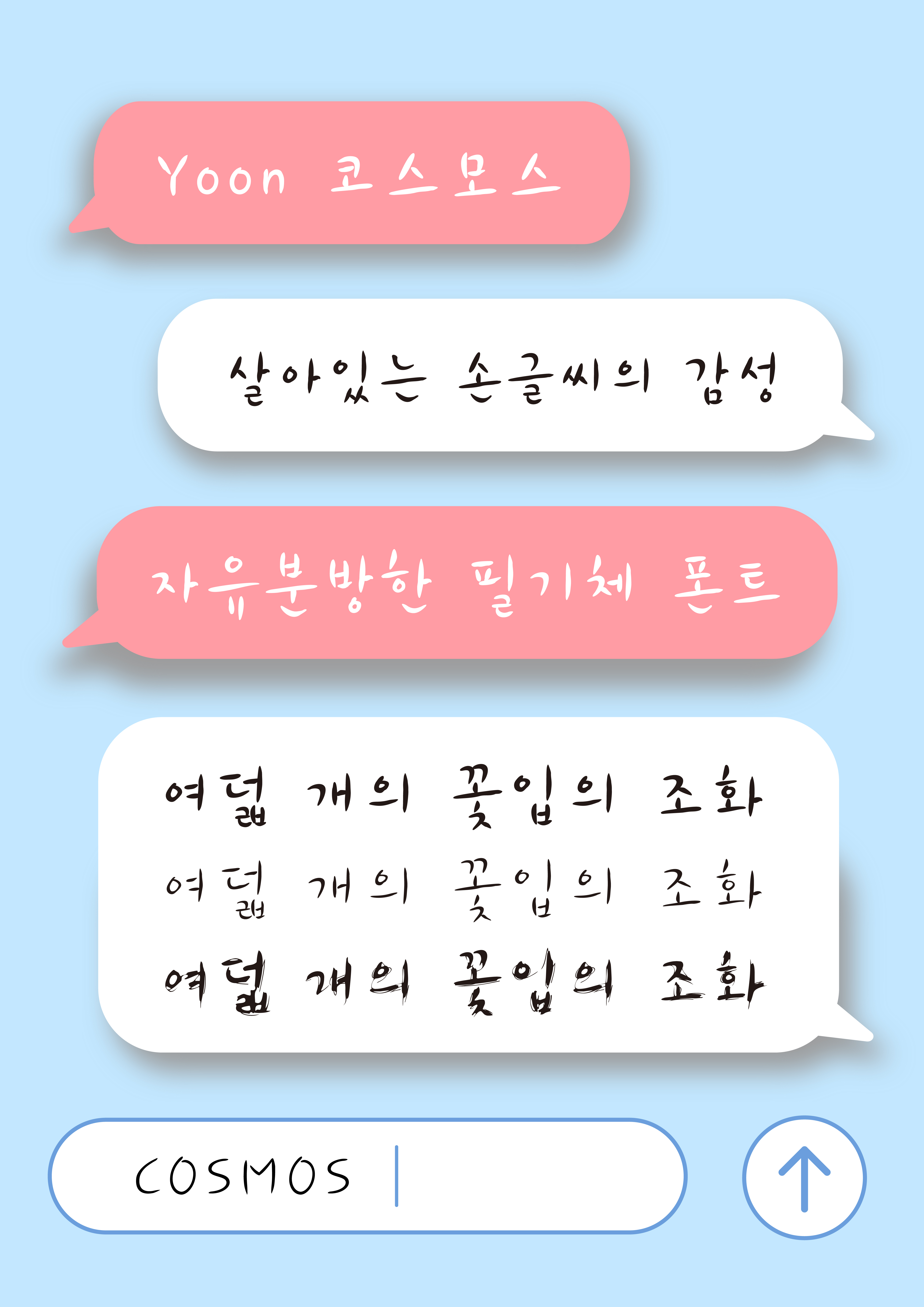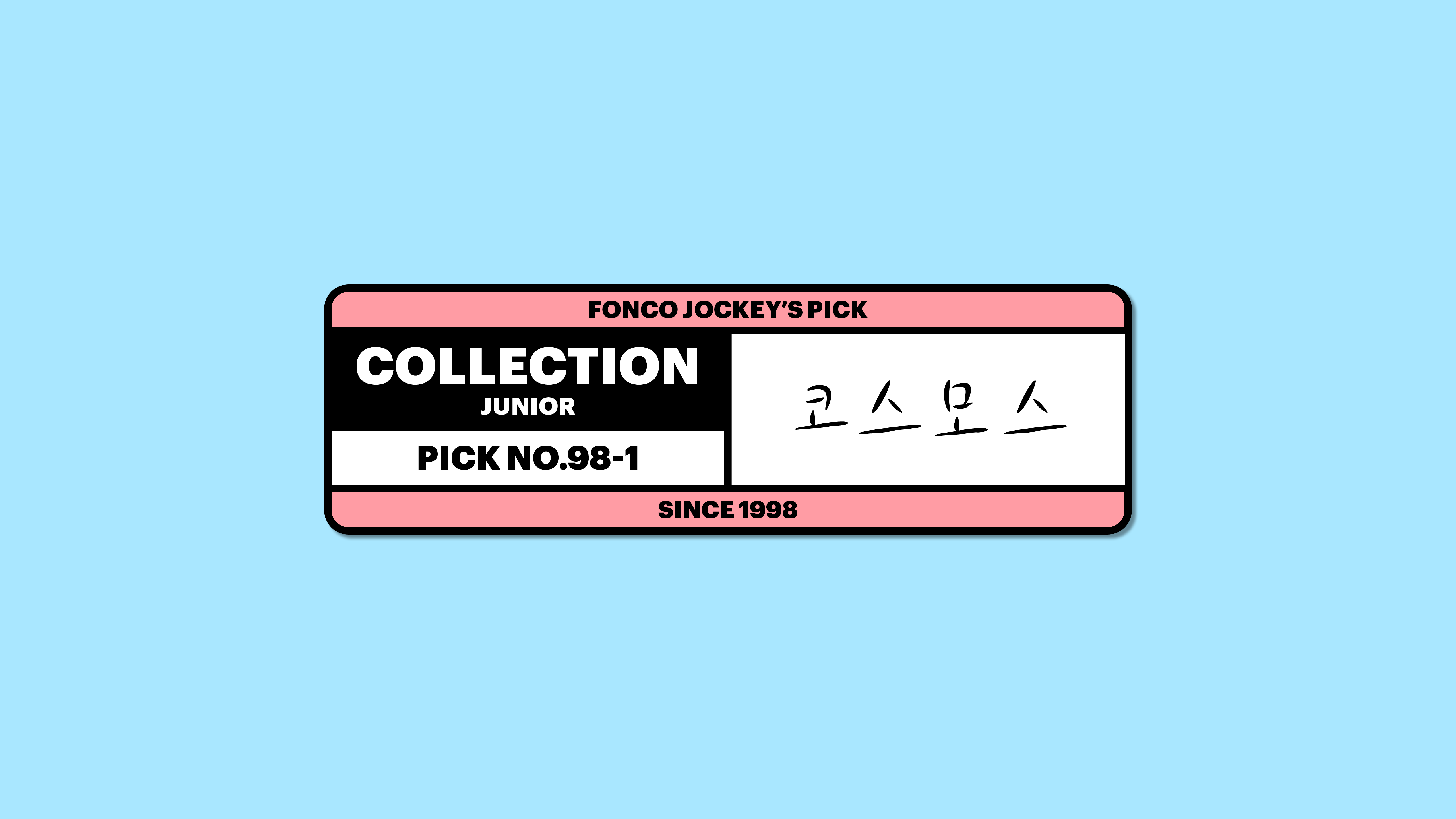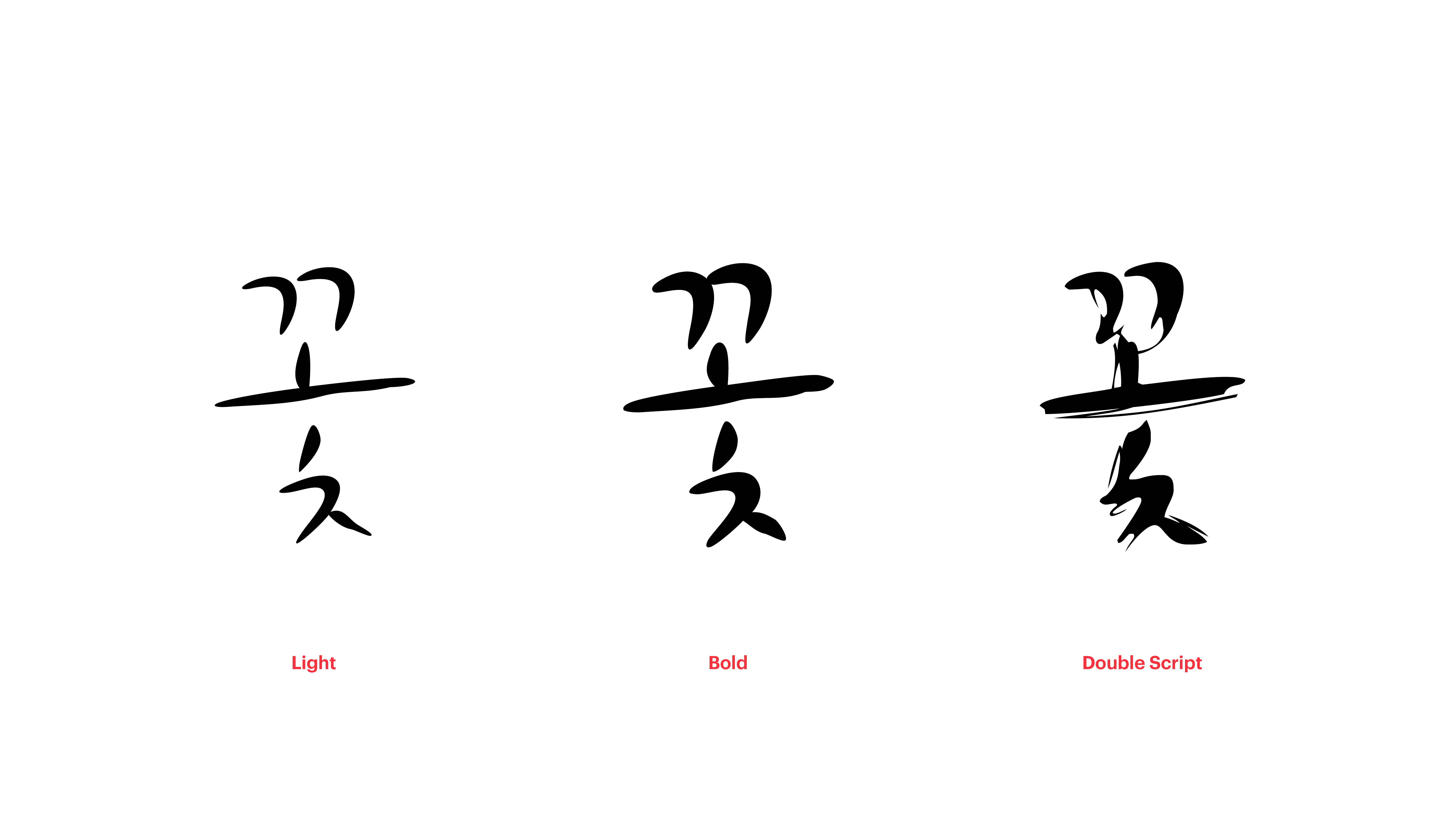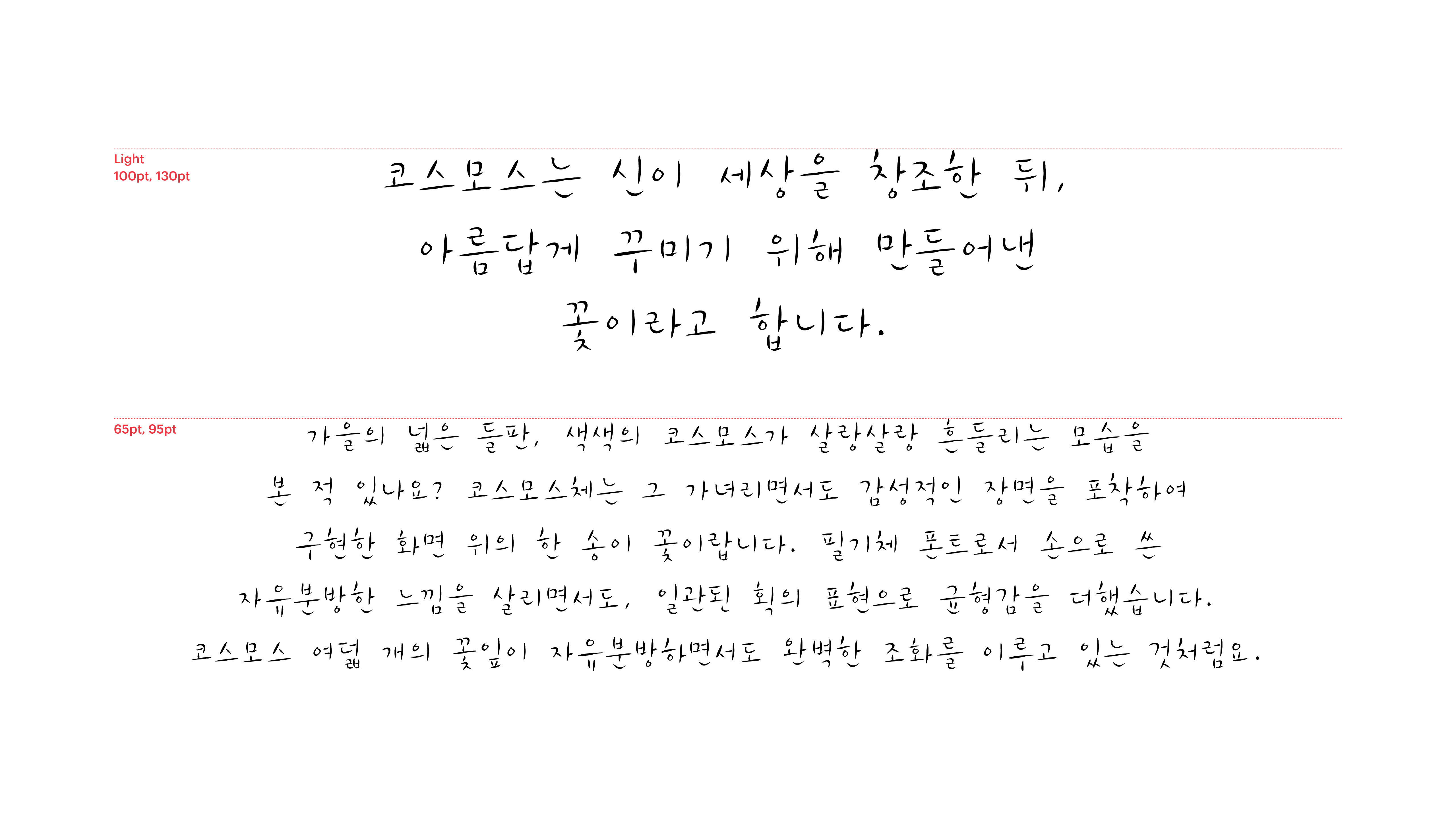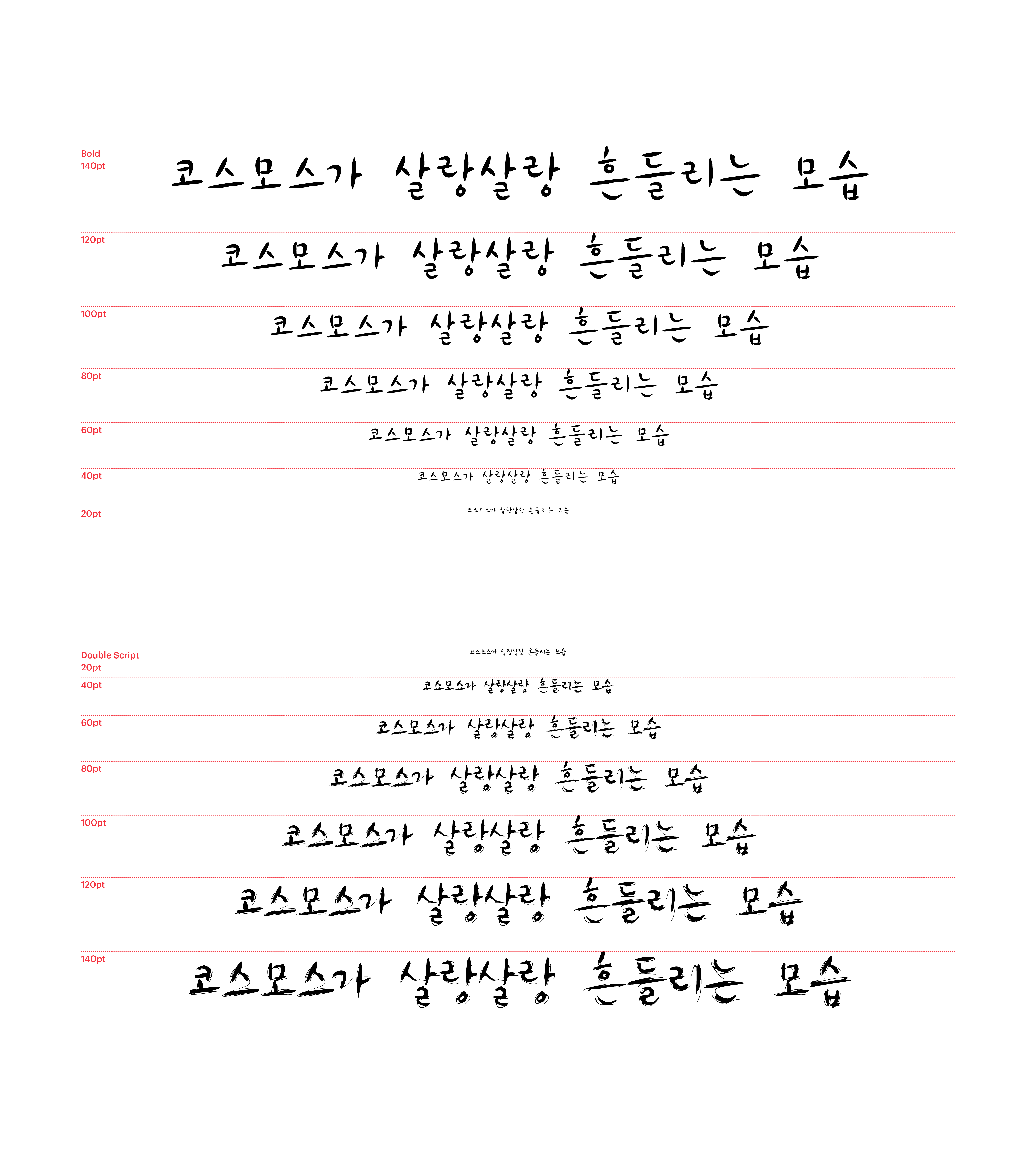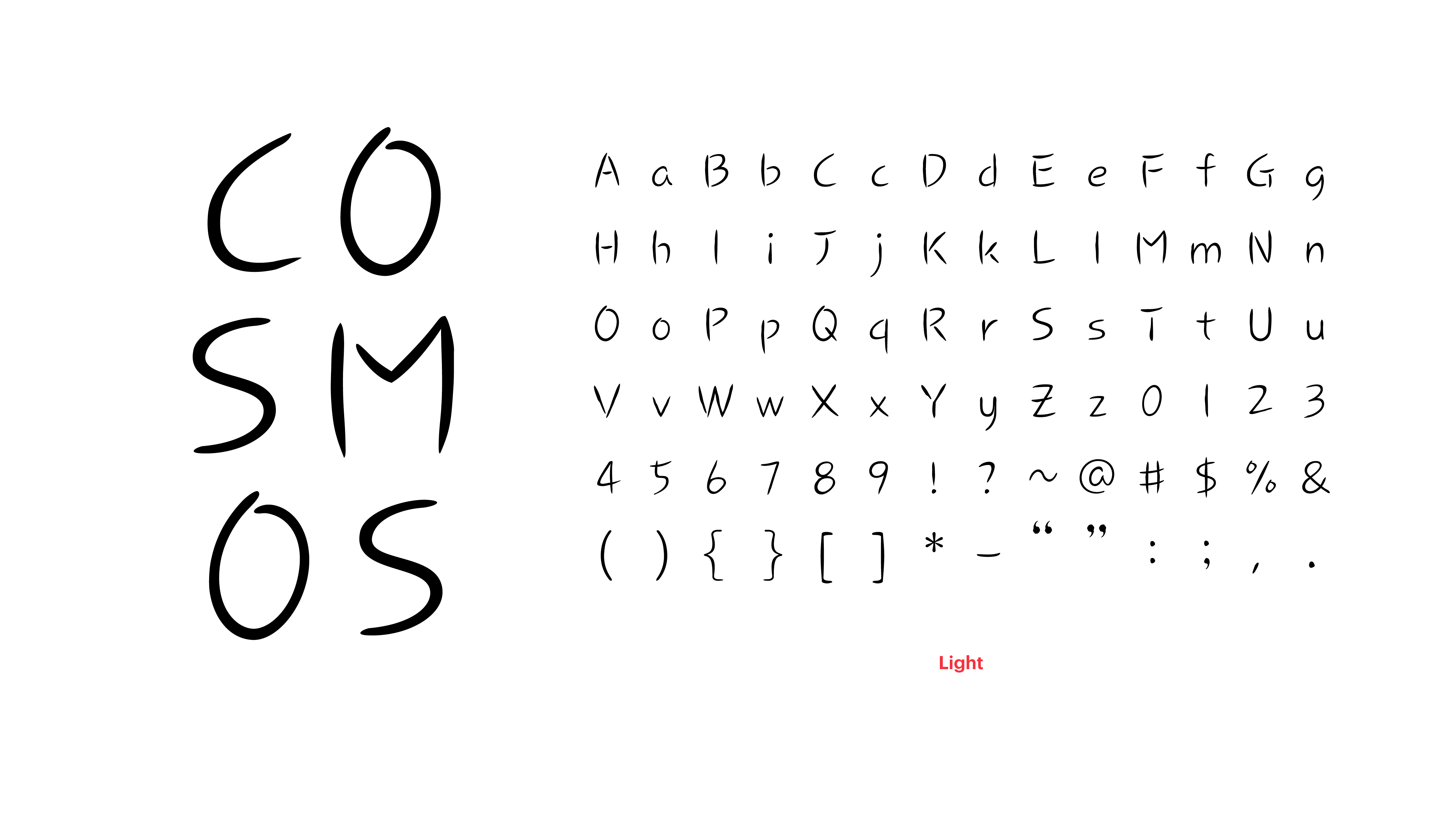
가을의 넓은 들판, 색색의 코스모스가 살랑살랑 흔들리는 모습을 본 적 있나요? 코스모스체는 그 가녀리면서도 감성적인 장면을 포착하여 구현한 화면 위의 한 송이 꽃이랍니다. 필기체 폰트로서 손으로 쓴 자유분방한 느낌을 살리면서도, 일관된 획의 표현으로 균형감을 더했습니다. 코스모스 여덟 개의 꽃잎이 자유분방하면서도 완벽한 조화를 이루고 있는 것처럼요.
Yoon 코스모스